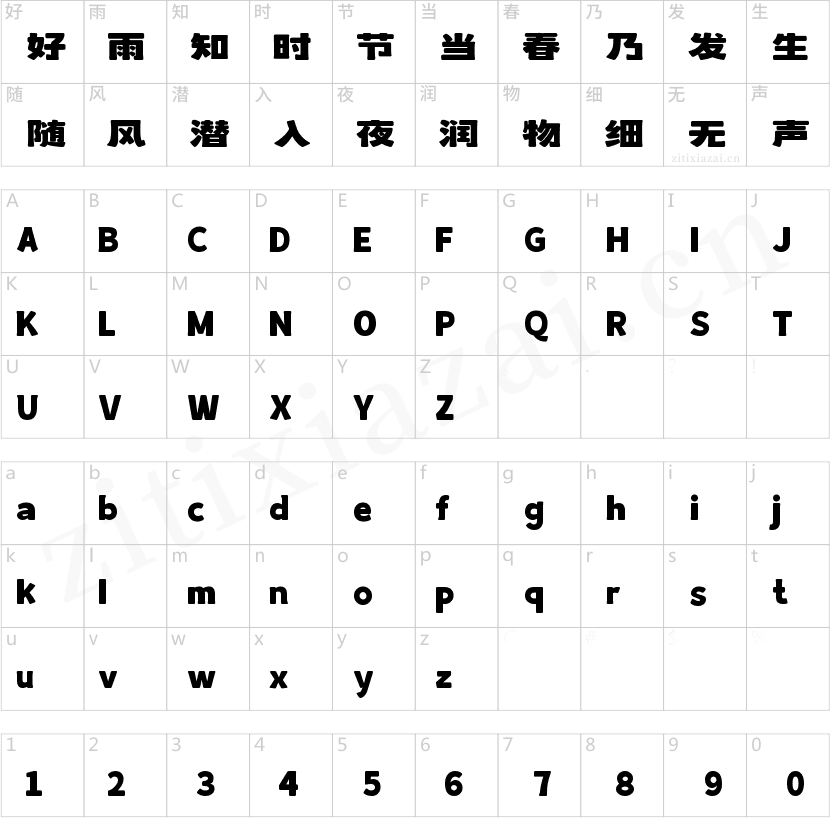
壹心悦游体
壹心悦游体,这款字体结构工整、笔画清晰,兼顾美观与易读性,适用于标题、正文、海报、包装、LOGO 等多种场景。字形优雅稳定,风格百搭耐看,适配日常排版与创意设计,让文字呈现更舒适、更具质感。壹心悦游体一笔一画,皆是细节,以均衡的比例、流畅的线条打造舒适视觉体验,字形端正大气,风格简约现代。无论是商业设计、品牌宣传还是日常排版,都能轻松驾驭,让文字更有格调与力量。壹心悦游体字体下载。